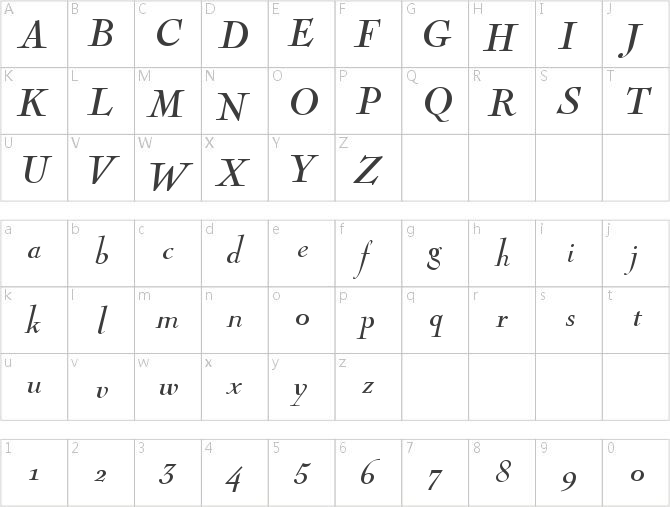
NicolasCocTEEReg-Italic 詳情頁
NicolasCocTEEReg-Italic字體字庫是一款讓人賞心悅目、百看不厭的英文字體,適合各類廣告和產(chǎn)品包裝設(shè)計應(yīng)用,字體大小0.05MB,格式為ttf字體,上傳用戶是順新廣告?,作者/版權(quán)方為未知